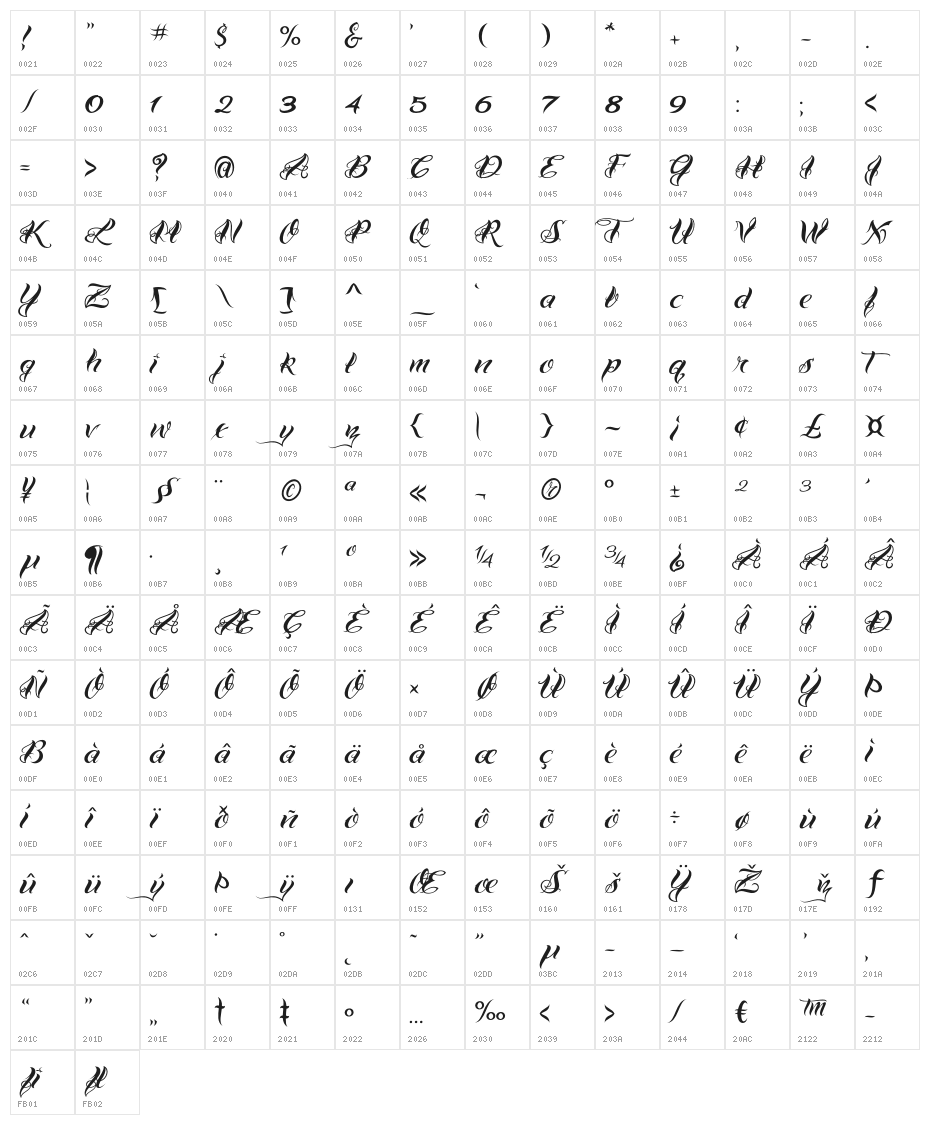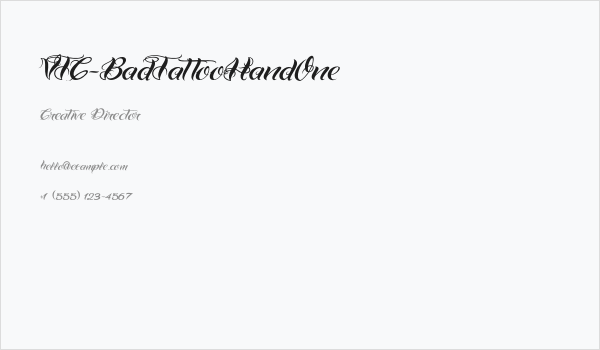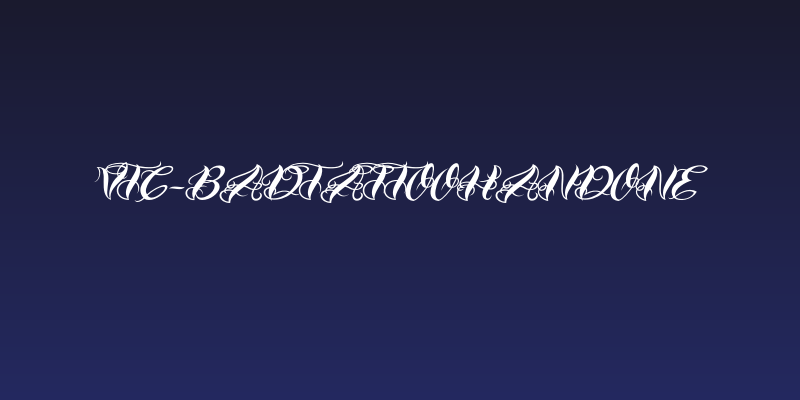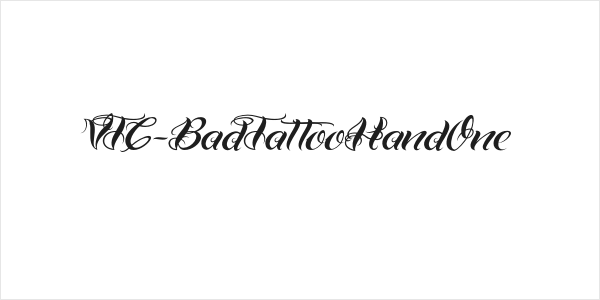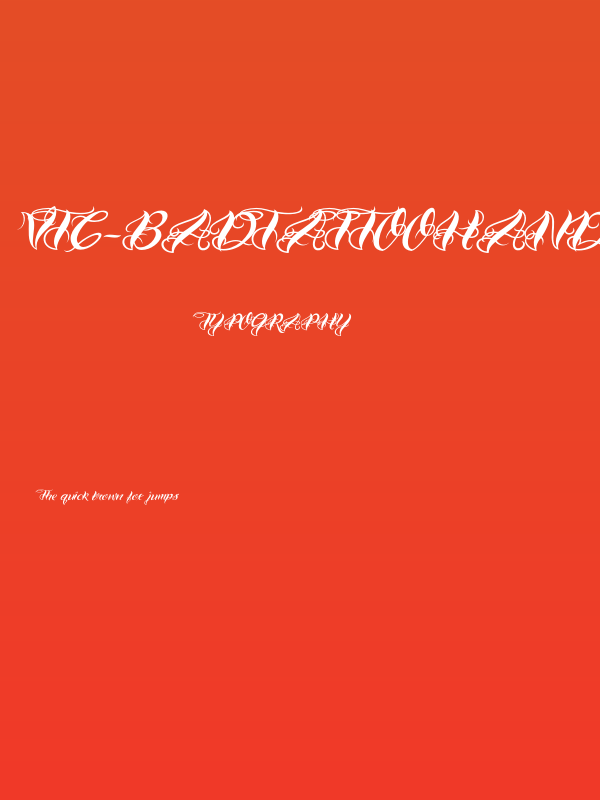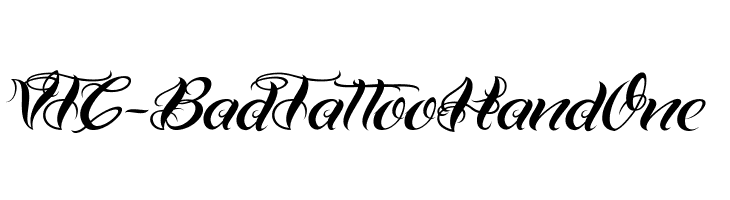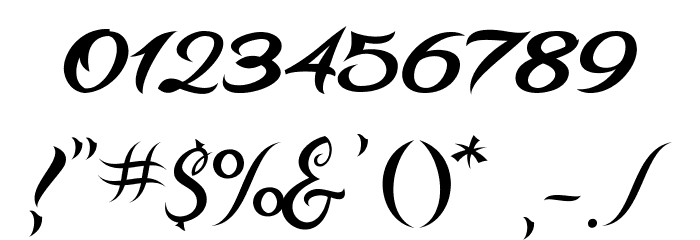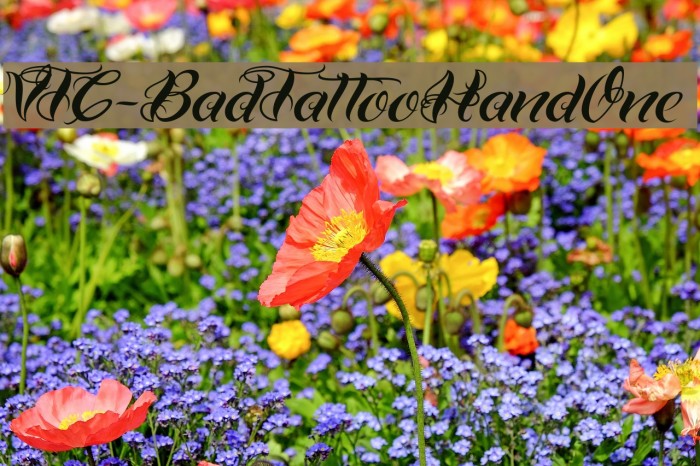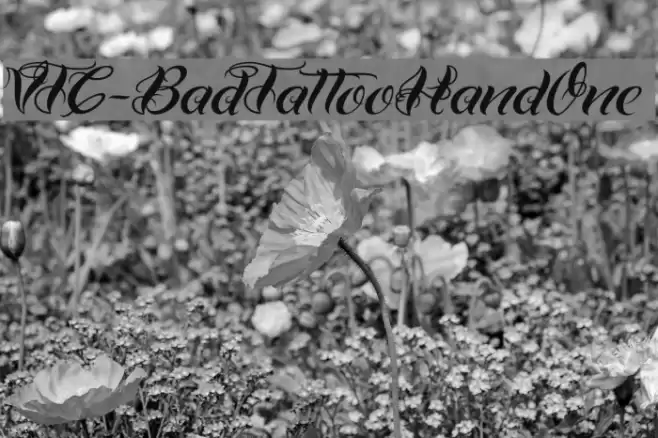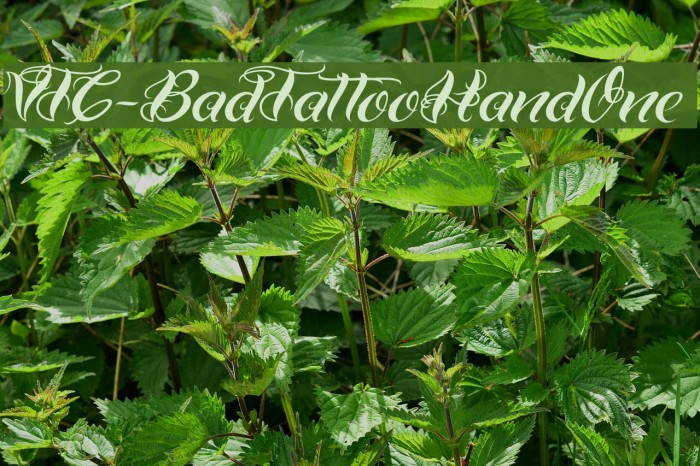
VTC-BadTattooHandOne Font
✎ Curly
| Anwendungsfall | Logos, Headlines, Posters |
| Vorgeschlagene Projekte | Ideal for tattoo designs, album covers, posters, and branding that requires a bold statement. |